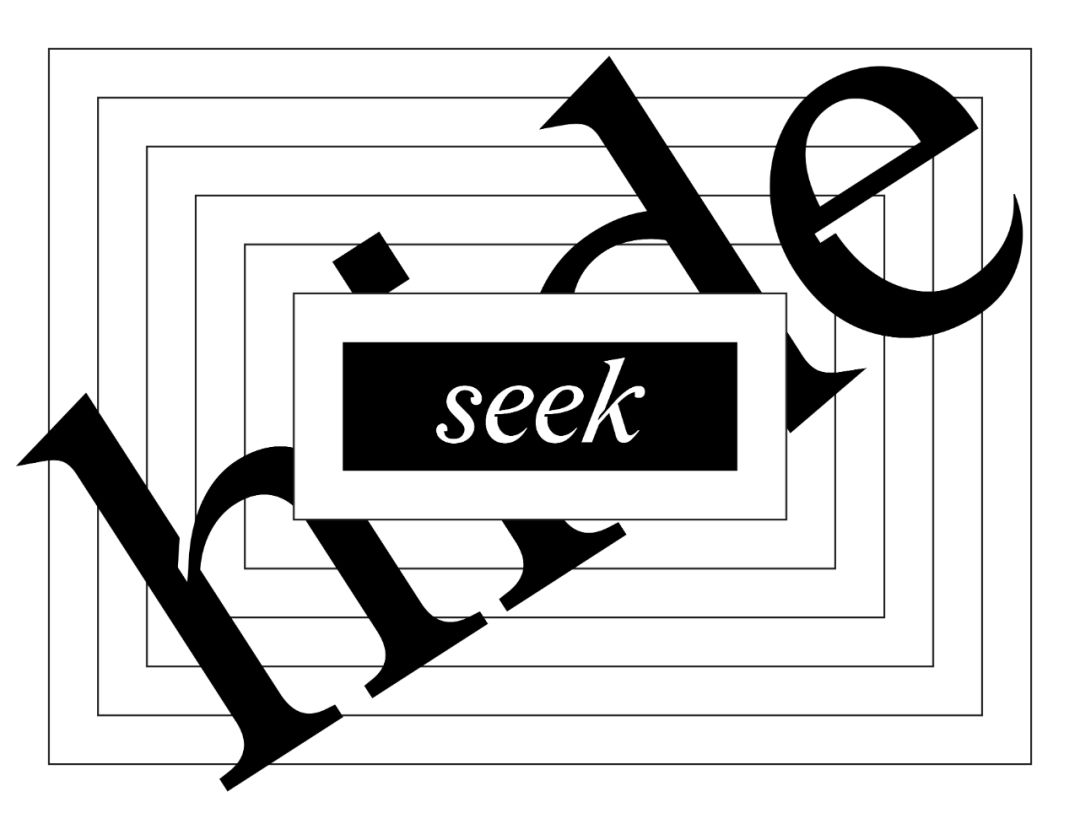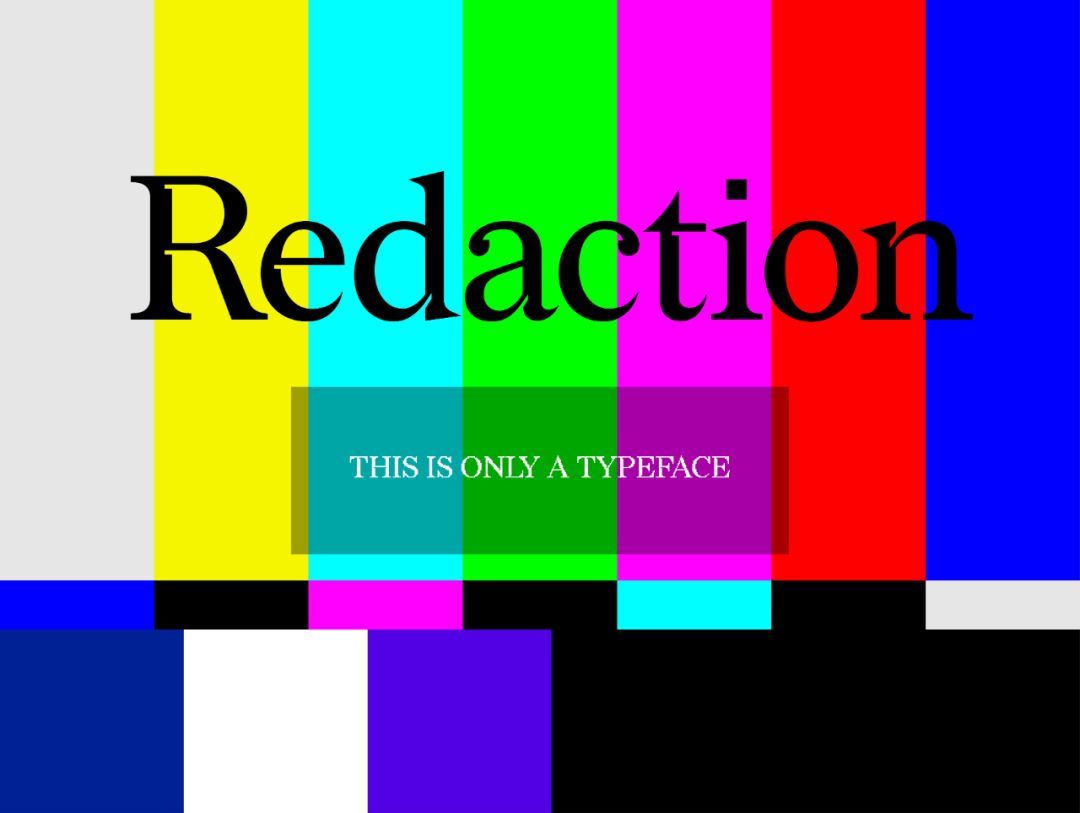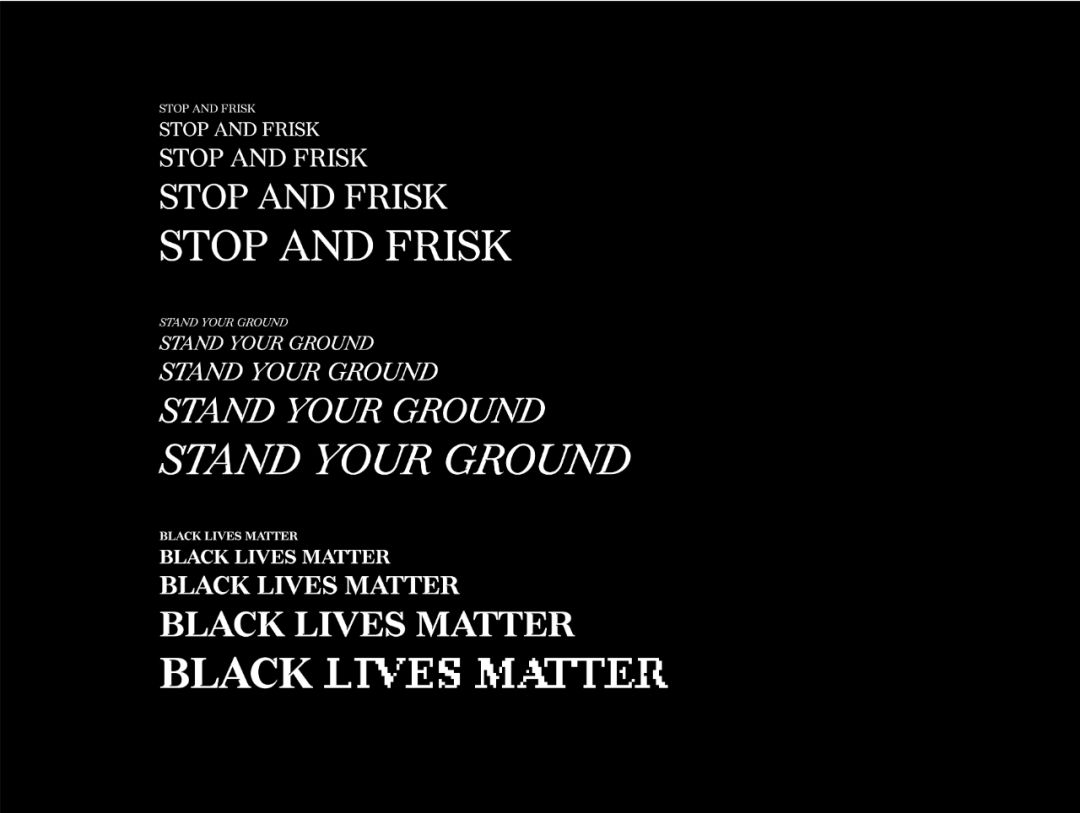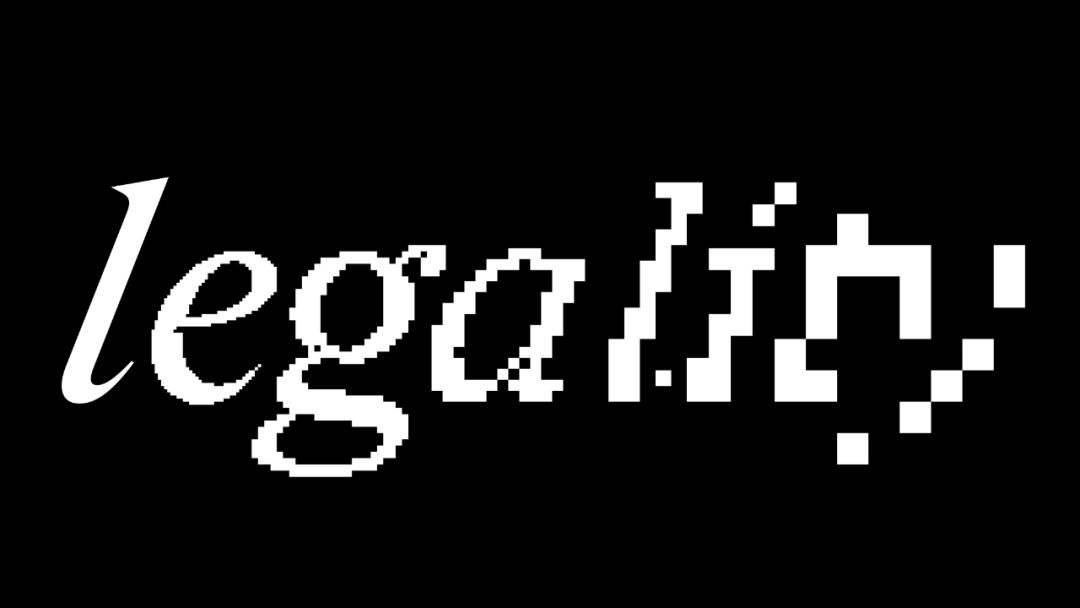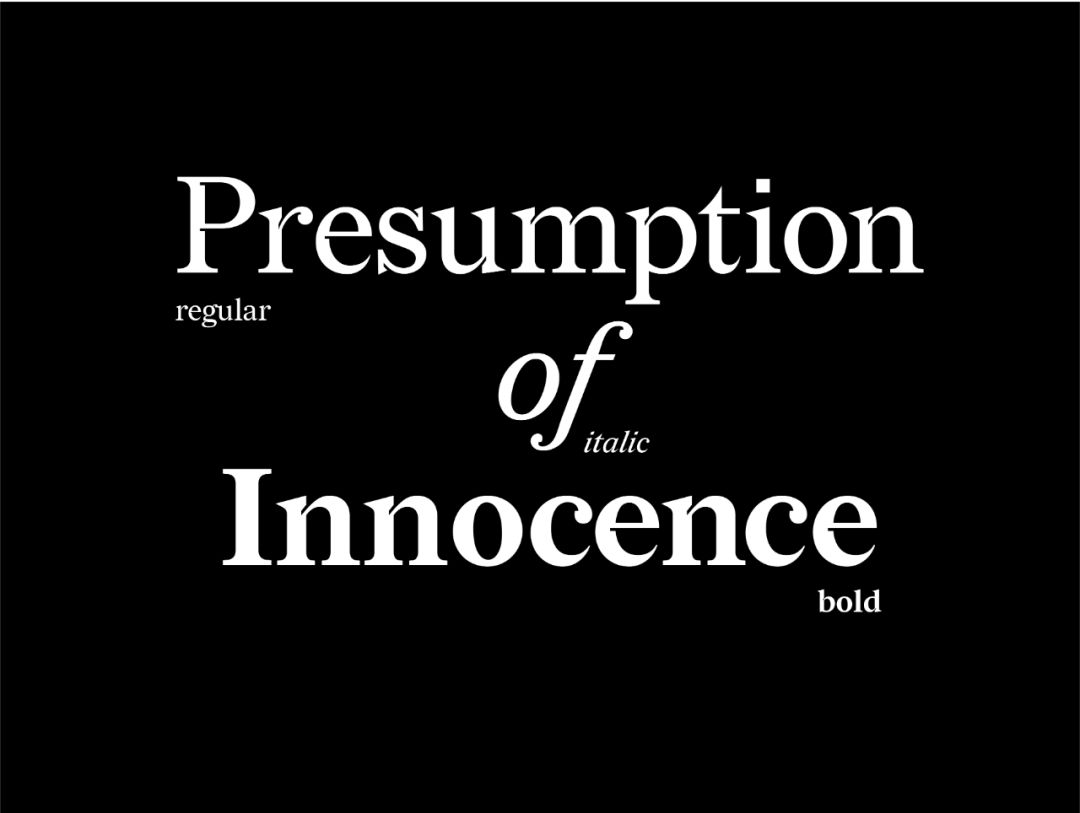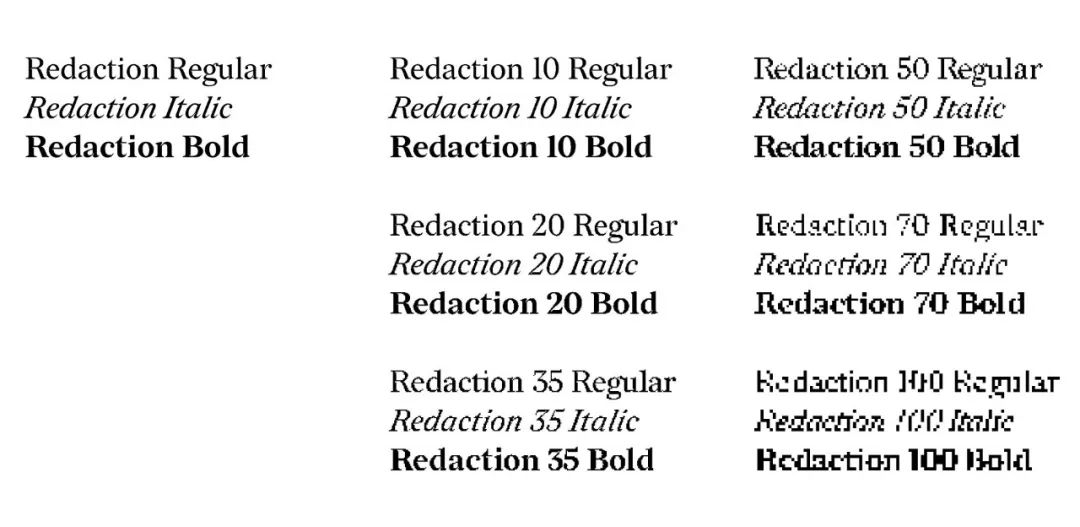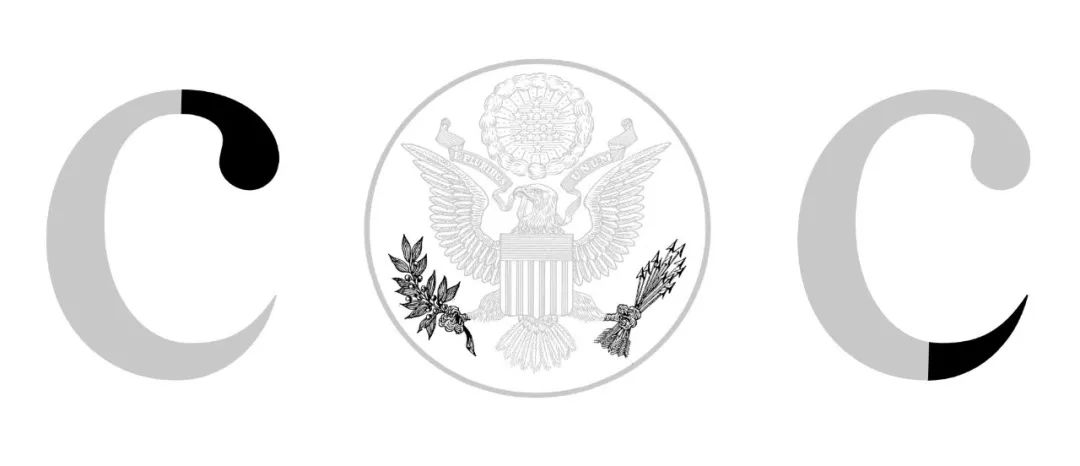
“修正”权威——尖锐再尖锐,模糊再模糊
尽管公众可能并没意识到
但“权威”就蕴藏在文本中
……
视觉艺术家兼电影制片人Titus Kaphar和传记作家、律师Reginald Dwayne Betts发起了一场名为“The Redaction(修正)”的项目,试图通过搜集法律文本中来突出刑事司法系统中的弊端,尤其是穷人和边缘化群体因未能支付法庭罚款和费用而被监禁的相关举措。
自然地,他们想到了邀请字体设计师来为这个项目设计一套独特的字体。而来自知名品牌设计公司Wolff Olins的全球负责人Forest Young和MCKL字体设计公司的创始人Jeremy Mickel就是他们的选择。
“修正(The Redcation)” by Forest Young & Jeremy Mickel
从粗体到斜体,从易读到难以辨认——就好像那些被反复复印的法律文件,文本逐渐模糊,甚至重要内容被涂抹、遮盖。
创作的第一阶段,Young和Mickel进行了大量的法律文本研究,尽可能多地了解法律文件的历史、性质,及它的多种修正方式:简单标注在黑框旁边;标记“已删除”字样;其他手写标记等。
通过翻阅大量历史法律文件,设计小组观察到了无数法律文本字体逐渐模糊、难以辨认的不同状态。
当文件被传真、影印或其他方式进行复制后,那些文字便被如何拉伸、膨胀、扭曲,直至看不出内容。这些文件可读性的变化也启发了“修正”字体的效果设计。
原始文本
依次是:传真机的数位图、照片采集、采样自模糊照片、高速扫描的粗糙数位图。
在美国,绝大多数的法律文件采用了Times New Roman字体。但是美国最高法院的官方要求是所有文件都必须用New Century Schoolbook。所以无论是Times New Roman,还是New Century Schoolbook,两者都是被人们“默认”的。尽管在文件中,文字看起来并不大,很难引起人们注意,但是这不妨碍它们充满“权威”的味道。
而这种“默认权威”感,正也是Young和Mickel所格外重视的。最终“修正”字体融合了两种字体,并将文本可读性在传播过程中的变化,提升到抽象概念,应用在“修正”字体的各个形式中。
在早期字体设计灵感中,美国总统的印章启发了设计团队——鹰的一只爪上抓着箭,一只爪上抓着橄榄枝。讽刺的是,这就像是法律体系中某些强烈对比的最强隐喻:残忍和同情;战争和外交;强硬与示弱;清白和黑暗……
这种对比逻辑很快被应用在“修正”字体中。柔软圆润变得尖锐锋利。夸张的对比加剧了紧张的情绪。
这些一系列的改变,不仅仅是一种简单的设计美学。从清晰易读,到难以辨认。“修正”字体各形式的变化,所体现的也是在一些刑事司法案件中,人们所面临的被边缘化。而法律文件的文字本应担起“权威可信”及“易读”的角色和责任。
是艺术?还是设计?
相比与商业设计及其他更能广泛使用的字体,“Redaction”字体似乎更像是一种艺术创作。
谈及这个问题,Young和Mickel回答——“它仍然是设计,为艺术服务的设计。”
在许多方面,它与商业客户项目是一样的,在最终工作中有客户、创意简报、反馈和修改轮次、截止日期和字体的使用,但这也是一个独特的机会。
和其他商业项目相同,“Redaction”的创作同样涉及“客户” “创意概念” “多轮的改稿” “截止期限” “字体的使用”等等诸多问题。但是不得不说,它也是一次极其特殊的创作,会掺杂设计师的个人情感、背后的社会信息等等个性化的东西。
超乎原本的项目需求,Young和Mickel共设计了“Redaction”常规体、粗体、斜体的三种形式,并制作了相关的自定义演示、调试动画、专门网站等等,极具互动性。
常规-自定义演示
加粗-自定义演示
斜体-自定义演示
是的,它仍然是设计,为艺术服务的设计。“Redaction”对公众的免费开放,可以使这些文本后的故事在更大程度上被人们听到和感受。同时,它允许“设计”进入一个更概念化的层次里。
字体可以承载丰富的历史和意义,尽管大多数人可能并不会注意到字体中的诸多细节,但是这并不代表“影响”并不存在。